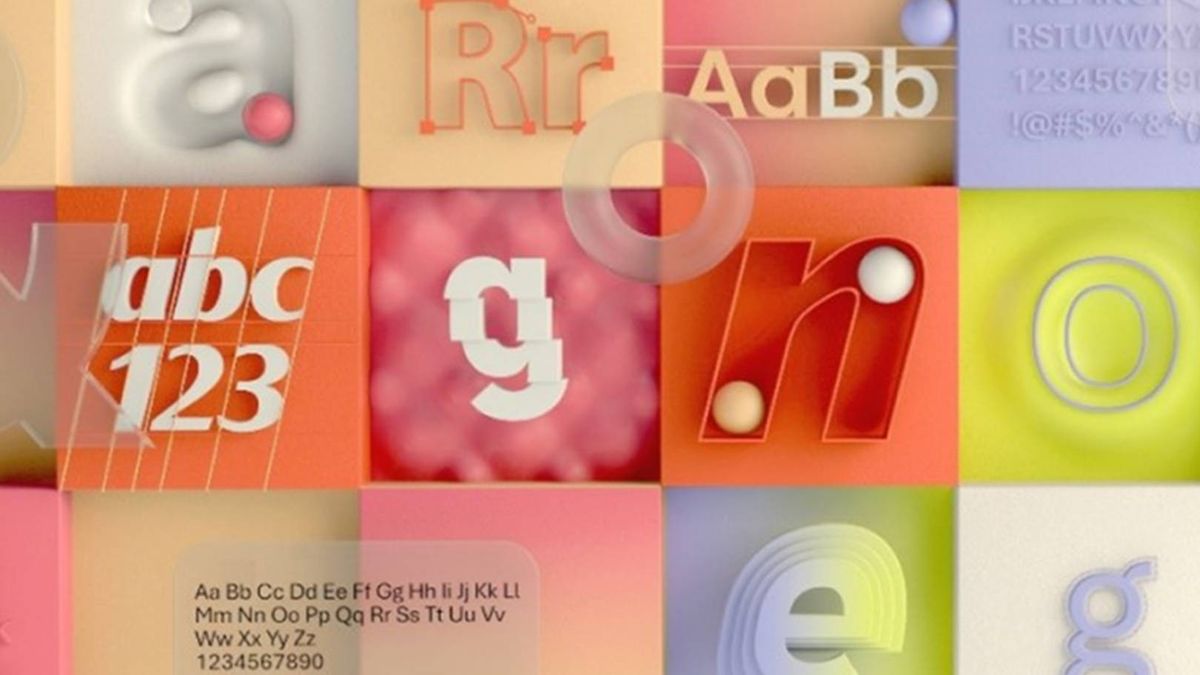
Calibri idzie na emeryturę - będzie nowy domyślny font w MS Office
14 lat temu Times New Roman został zastąpiony przez Calibri na pozycji domyślnego fontu w pakiecie Microsoft Office. Amerykański gigant doszedł do wniosku, że czas na kolejną zmianę.
W ciągu ostatnich 14 lat sporo się zmieniło i nie potrzebujemy już aż tak zwartego fontu jak Calibri. Dlatego też Microsoft szuka dla niego następcy, chcąc równocześnie zachować jego najważniejsze cechy, a więc prostotę, czytelność i uniwersalność. W końcu domyślny font powinien być taki, by nie trzeba było poświęcać mu zbyt wiele uwagi i by w większości przypadków był po prostu optymalną opcją.
Nowy domyślny font w MS Office – oto kandydaci
W ten sposób Microsoft wytypował pięć fontów, które według niego najlepiej sprawdzą się w roli domyślnego kroju w programach Microsoft Office: Microsoft Word, Microsoft Excel czy Microsoft PowerPoint. To Skeena, Tenorite, Grandview, Seaford i Bierstadt. W każdym przypadku mówimy o foncie bezszeryfowym, a więc pod tym względem nic się nie zmieni.
Skeena najbardziej przypomina Calibri – to niewiele mniej zwarty font, ale nieco bardziej krągły. Skoro już przy krągłościach jesteśmy, to warto zwrócić uwagę na Tenorite z zupełnie okrągłymi literami i szerokością zwiększającą czytelność. Następny w kolejce Grandview ma zdecydowanie najbardziej techniczny wizerunek, przez co wydaje się najmniej praktyczny. Wiele osób mogłoby też mieć problemy z przekonaniem się do Seaford – przede wszystkim ze względu na bardzo charakterystyczne „k” i optycznie nierówną wysokość znaków. Wreszcie mamy też Bierstadt – ten font wydaje się najbardziej uniwersalny. On i Grandview ma też coś, co zdecydowanie przemawia na ich korzyść – to małe „l” (jak lis) zupełnie inne niż duże „I” (jak Irena).
Calibri ustąpi miejsca, ale nie zniknie
Calibri wkrótce przestanie być domyślnym fontem, ale oczywiście nadal bez problemu z niego skorzystamy, wybierając go z listy rozwijanej. Znajdziemy też na niej naturalnie wszystkie te kroje, które Microsoft wytypował w roli kandydatów na font domyślny, a które nie dostąpią jednak tego zaszczytu.